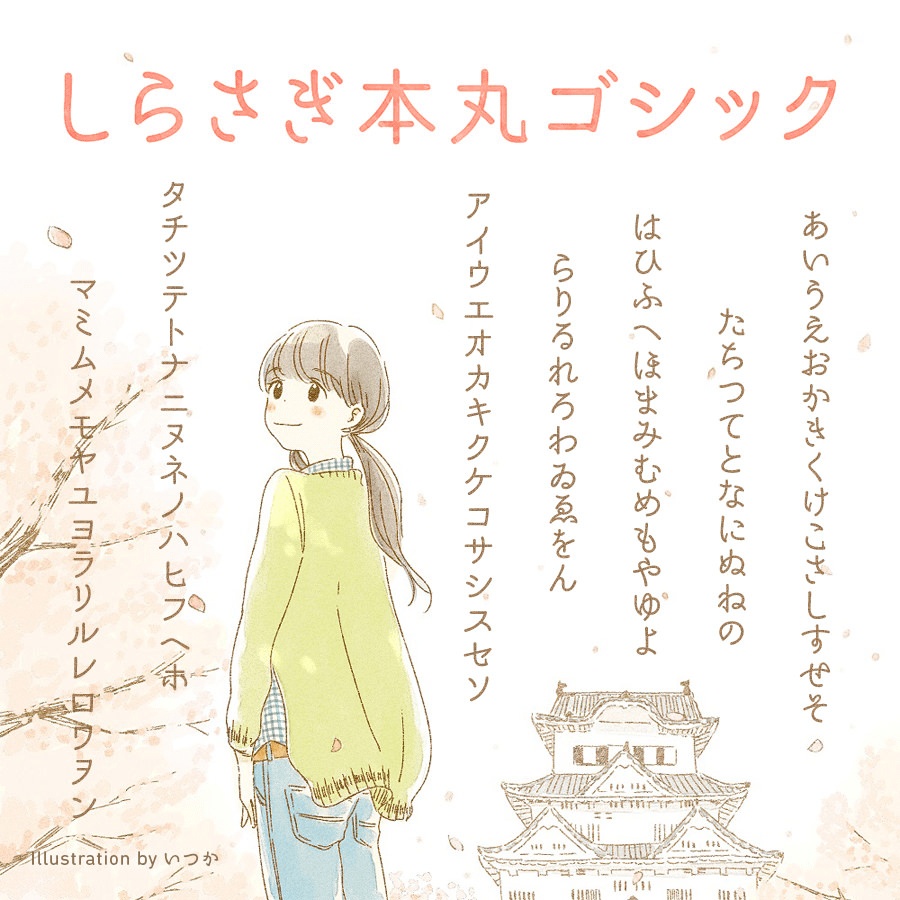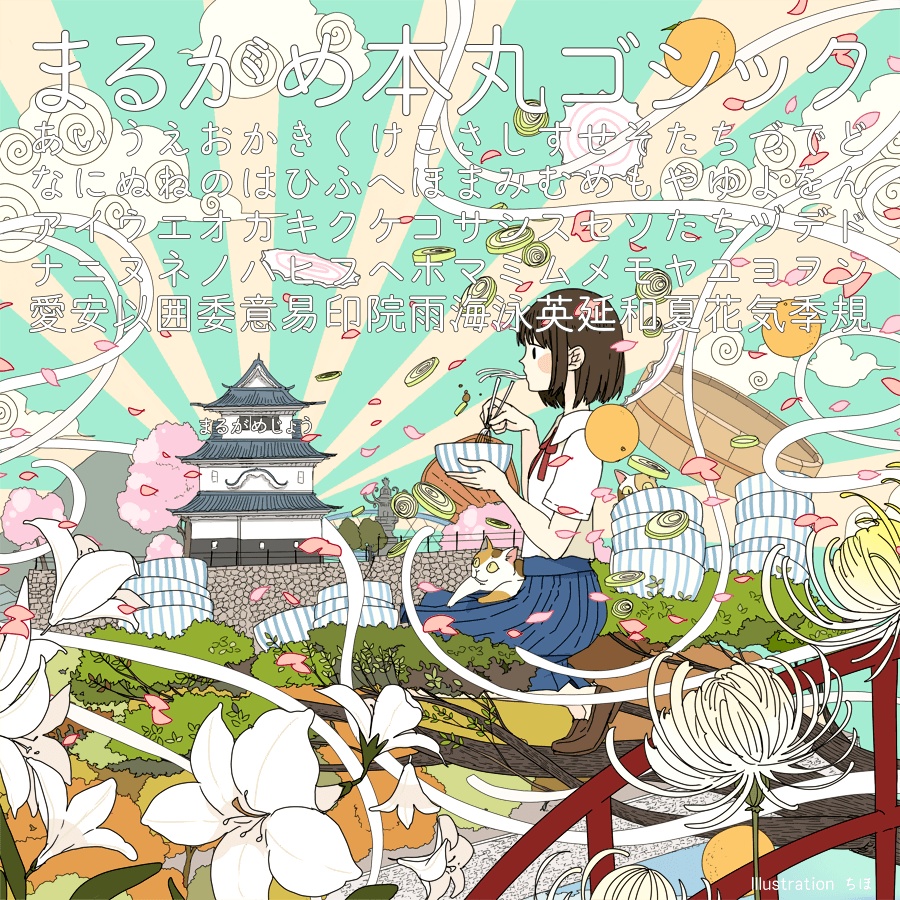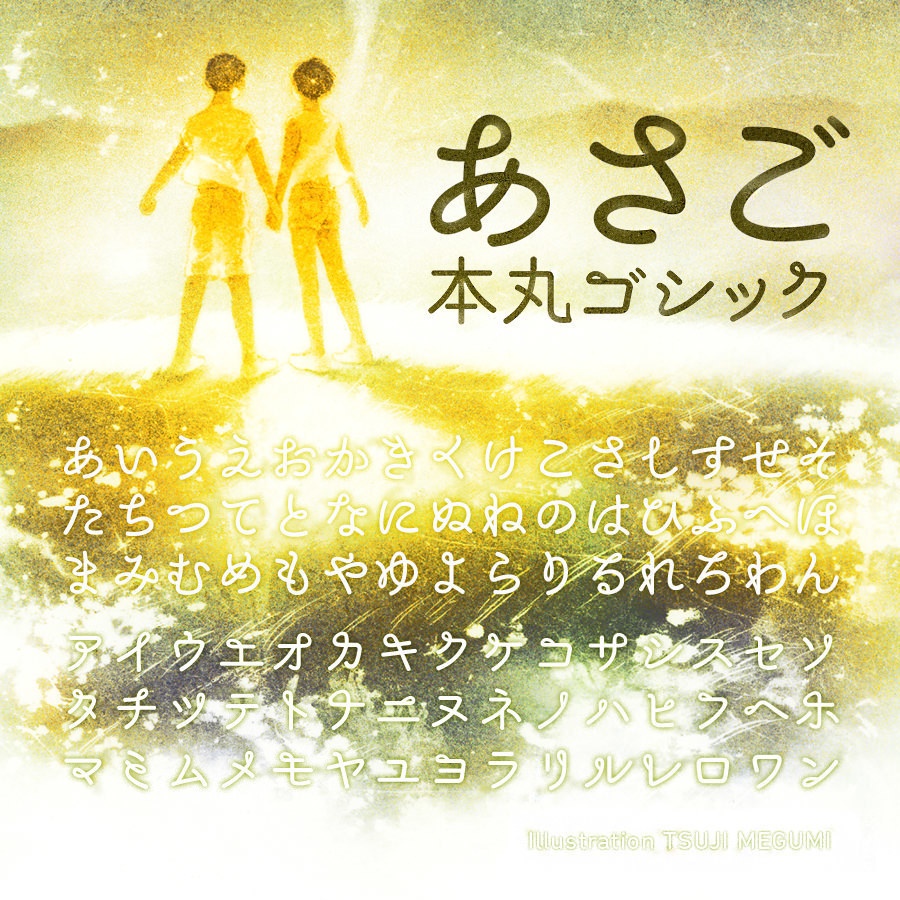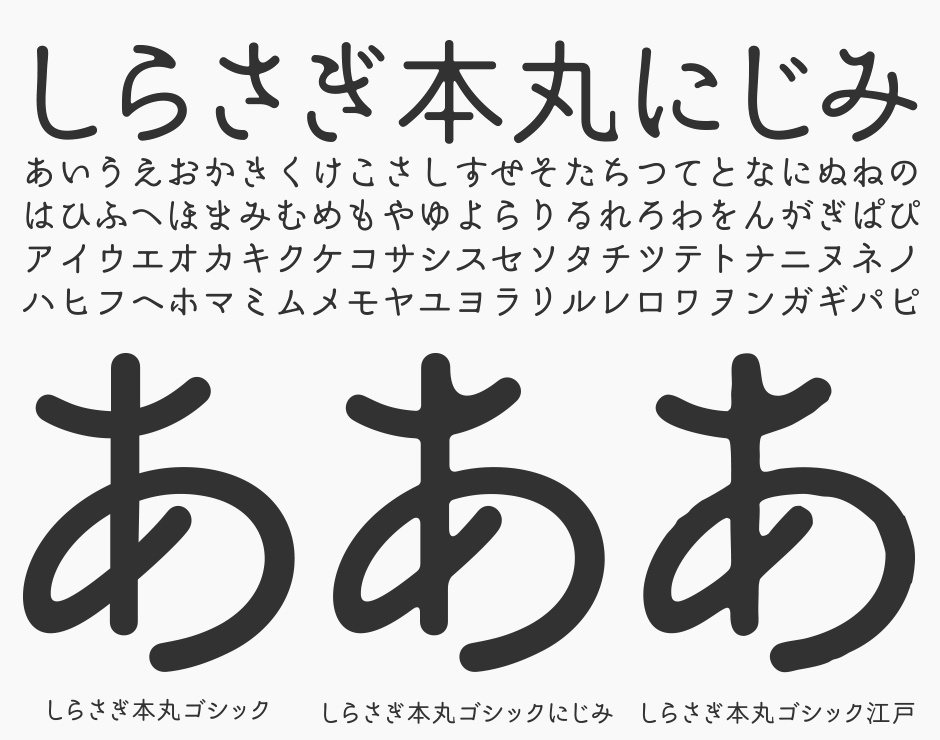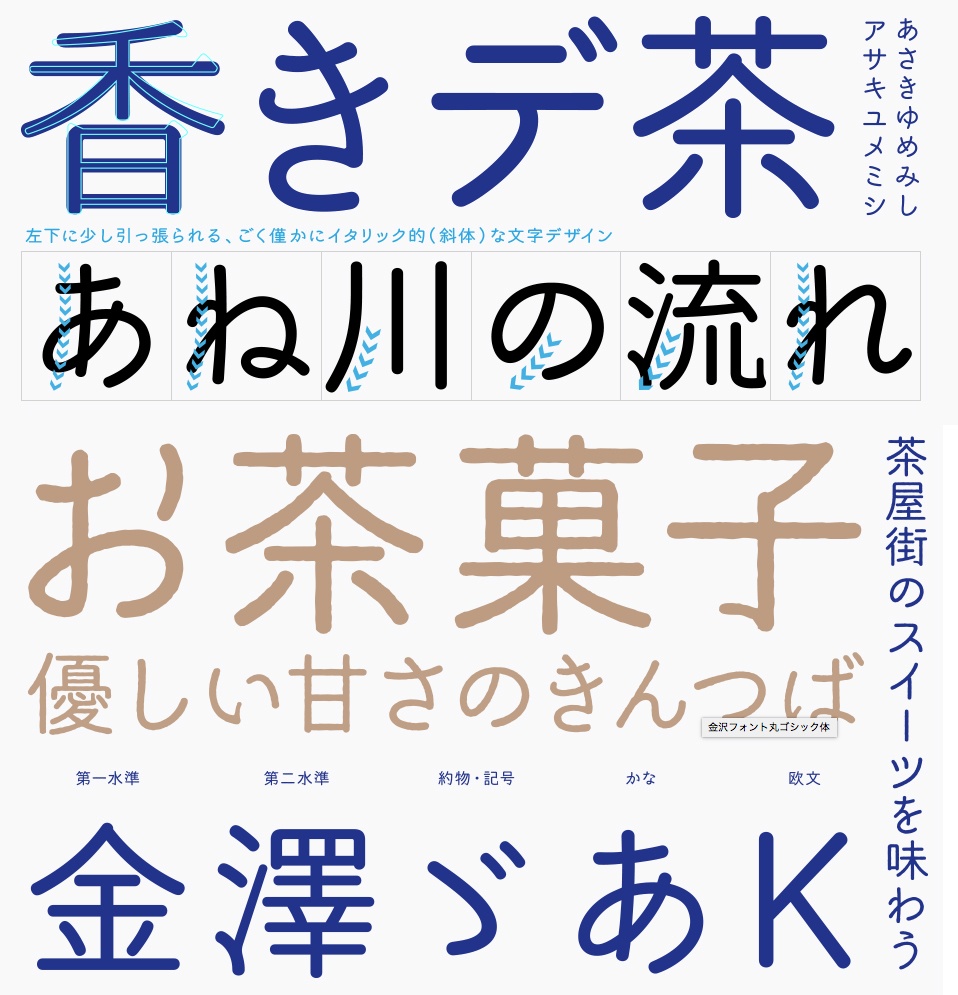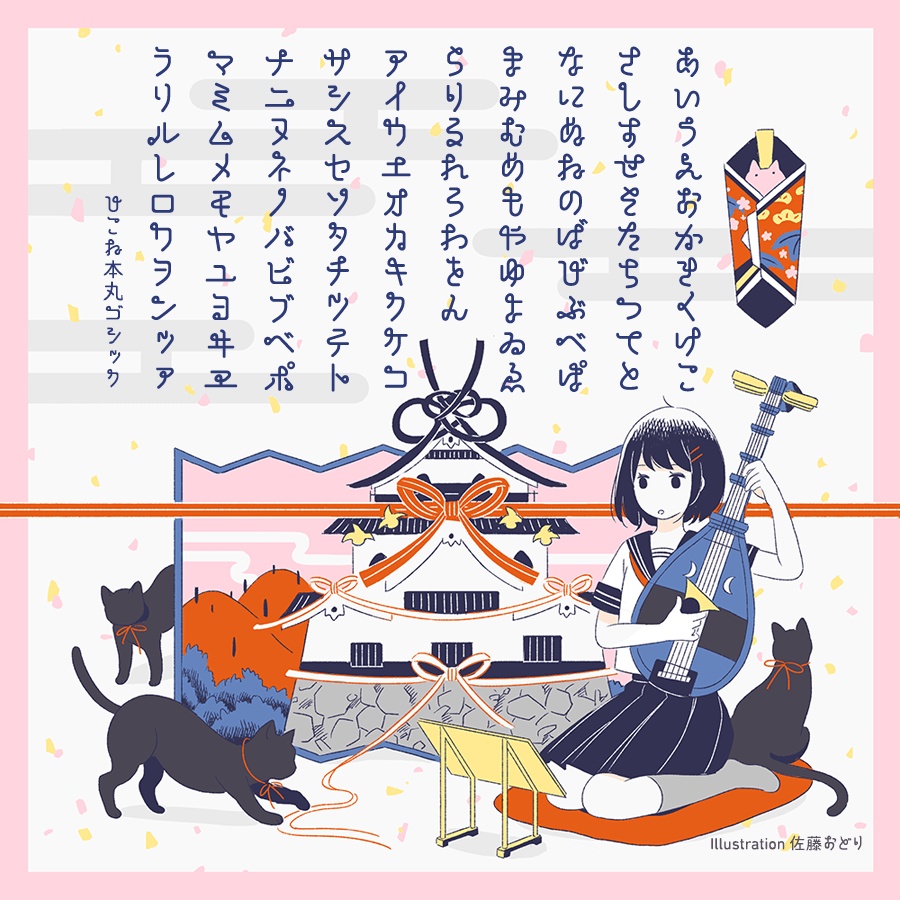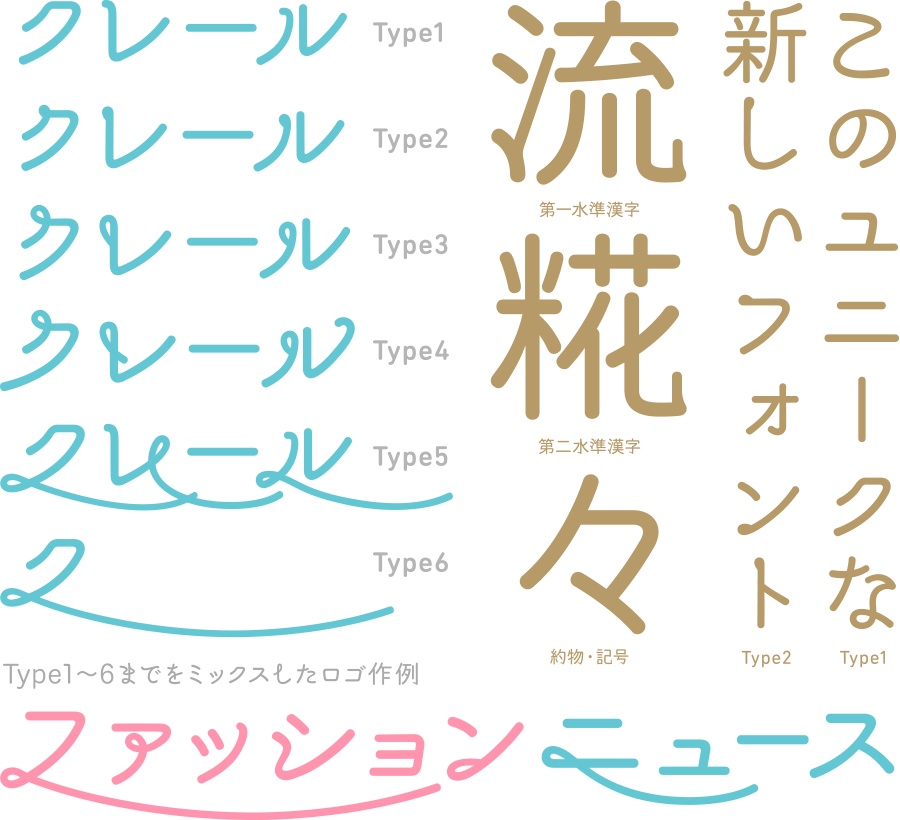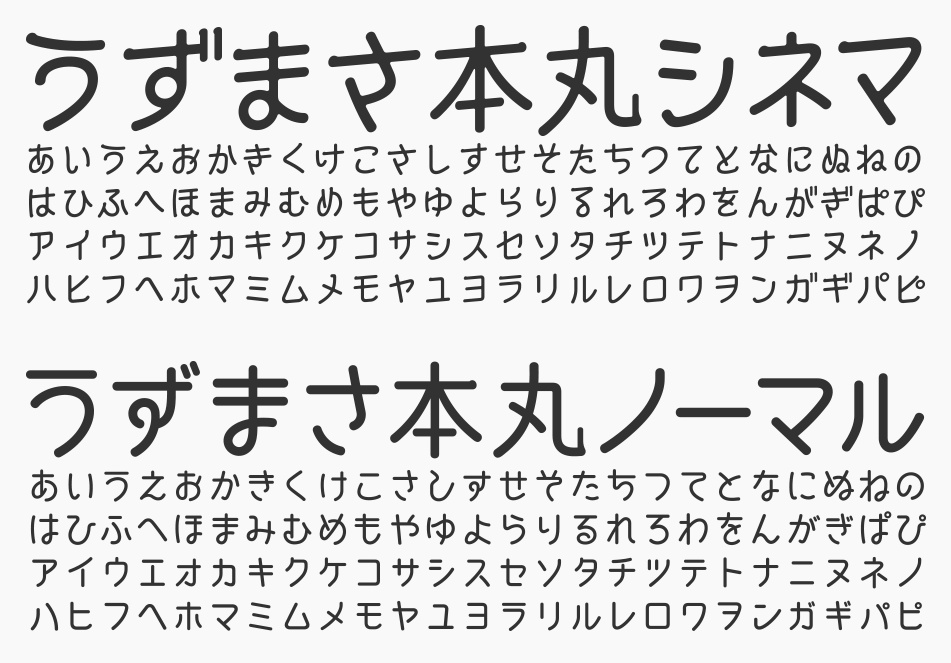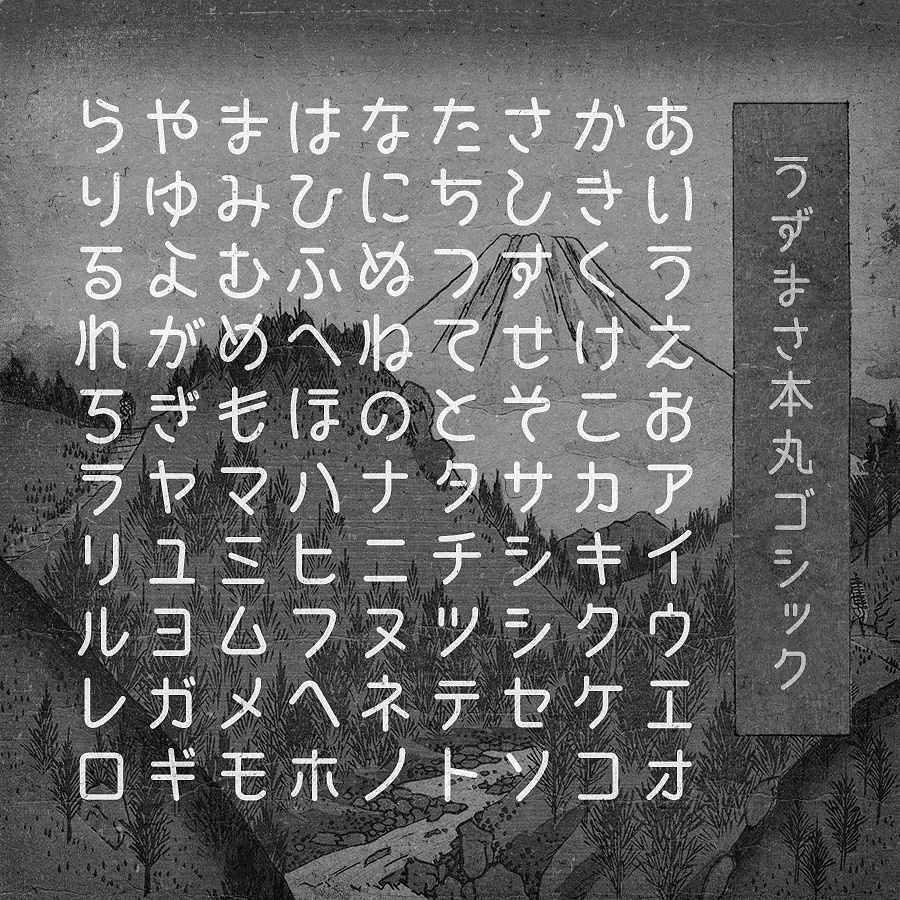
本丸ゴシックSET(全26フォント)
本丸ゴシック 日本の城下町をイメージした丸ゴシック体のフォント集 まるがめ本丸ゴシック体は少し物足りないような可愛さを追求。かなざわ本丸ゴシックは武家好みの形の中に、躍動感のある華麗な美しさがあります。あさご本丸ゴシックは山城の雲海に浮かぶような幻想的な美しさを表現しました。うずまさ本丸ゴシックはレトロな字幕・テロップの文字にピッタリです。しらさぎ本丸ゴシックは軽やかな印象を生み出します。迷路のような個性的なひこね本丸ゴシック。あなたのクリエイティブを刺激する全26フォント。日本タイポグラフィ年鑑2017入選。 収録フォント(26フォント) まるがめ本丸ゴシック(レギュラー)、まるがめ本丸ゴシックうどん(白抜き) かなざわ本丸ゴシック(レギュラー)、かなざわ本丸ゴシック茶菓子(ラフ) あさご本丸ゴシック(レギュラー)、あさご本丸ゴシック(Type1〜Type6)6書体 うずまさ本丸ゴシック(レギュラー)、アニメ、シネマ、シネマ斜体、ノーマル 5書体 しらさぎ本丸ゴシック、しらさぎ本丸ゴシックにじみ、しらさぎ本丸ゴシック江戸(3書体) くまもと本丸ゴシック(レギュラー)、くまもと本丸ゴシック春・夏・秋・冬(5書体) ひこね本丸ゴシック(レギュラー)、ひこね本丸ゴシック地、ひこね本丸ゴシック天 動作環境 Mac:システム/OS X対応(10.x)〜最新のMac OS Windows:OS/日本語版Windows2000、XP、VISTA、Windows7、Windows8、Windows10 フォント形式:OpenTypeフォント、TrueTypeフォント 収録文字数について 収録文字数4,072文字(第一水準2965文字+第二水準460文字+ひらがな.カタカナ.約物.記号.アルファベット等647文字)詳細 安心して使えるロイヤリティフリーの書体 あらゆる商用・デザイン用途(印刷物・ゲーム・アプリ・映像・動画・ロゴ・同人作品)に使用できる、商用申請の必要のないロイヤリティフリーの書体になります。文字の加工・変形も可能です。当シリーズにフォントが追加された場合は値上げ分の差額でいつでもアップデート可能です。ご安心ください。 1商品(1ライセンス)につき1ユーザー1PCのみがご利用いただけます。複数人で使用する場合は人数分をご購入ください。 フォント詳細はHPにも記載 https://www.flopdesign.com/shop/honmaru.html